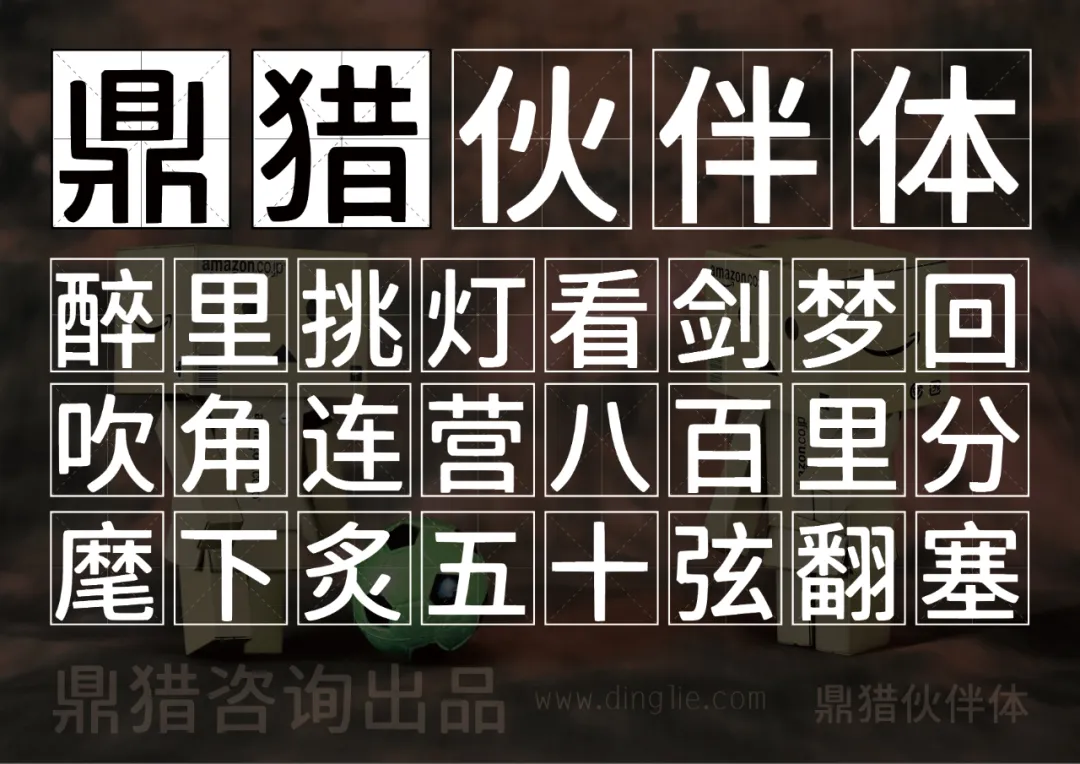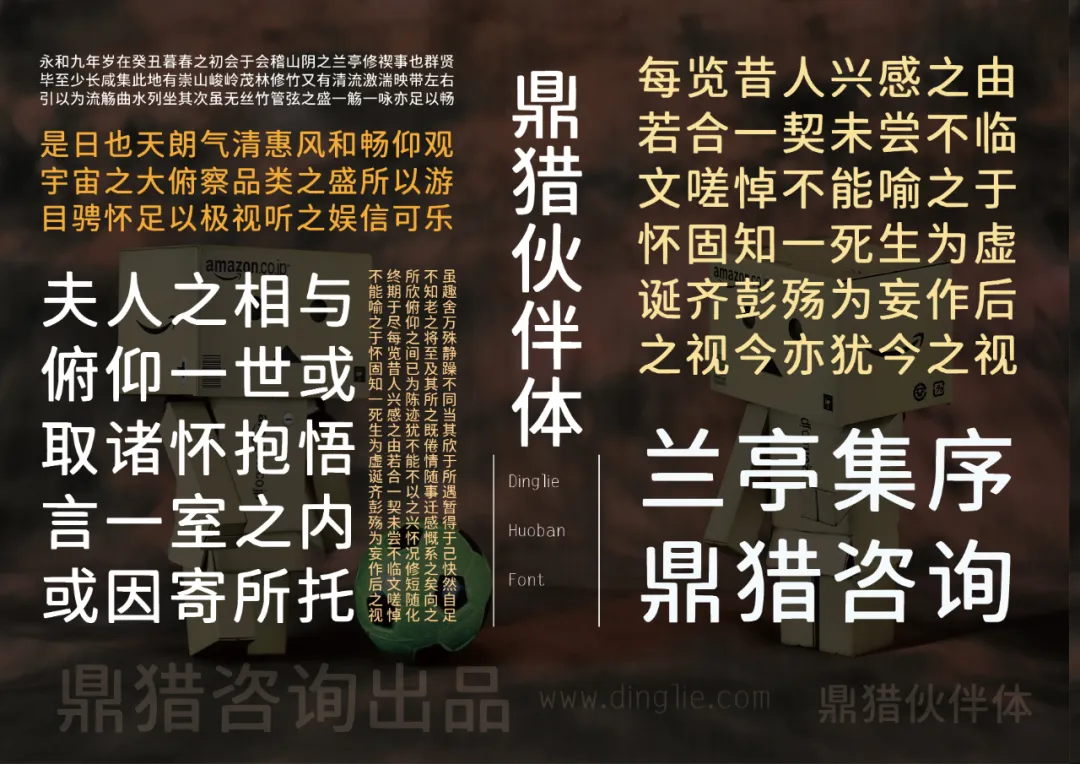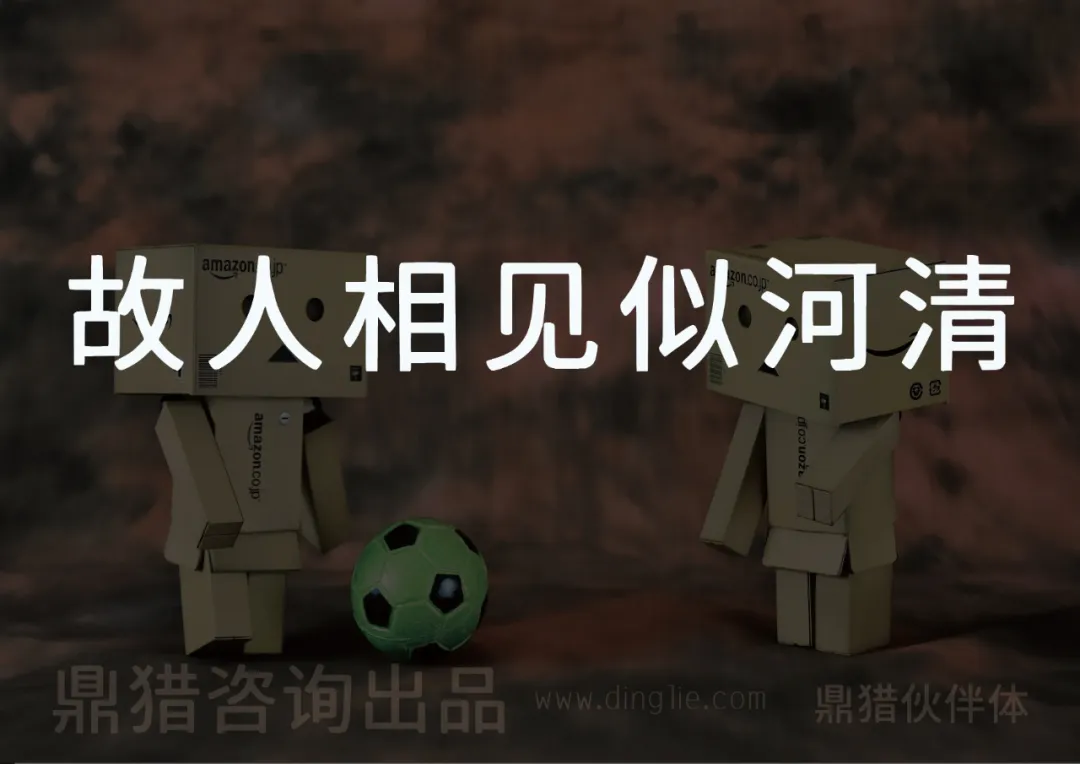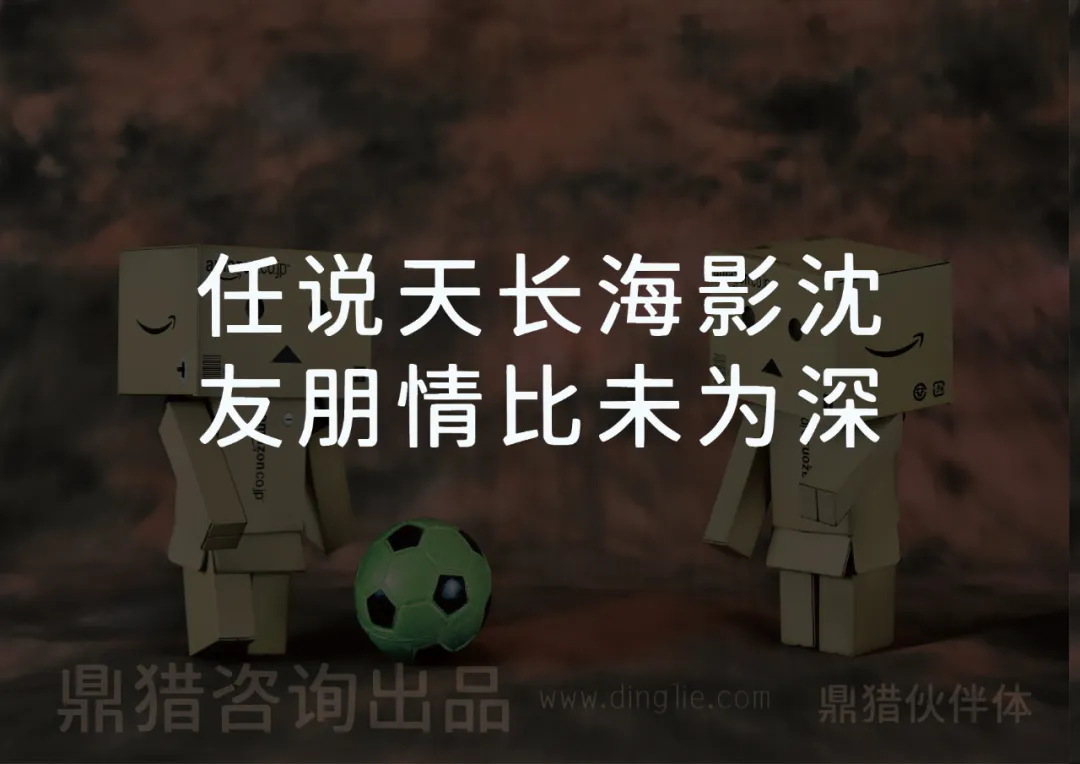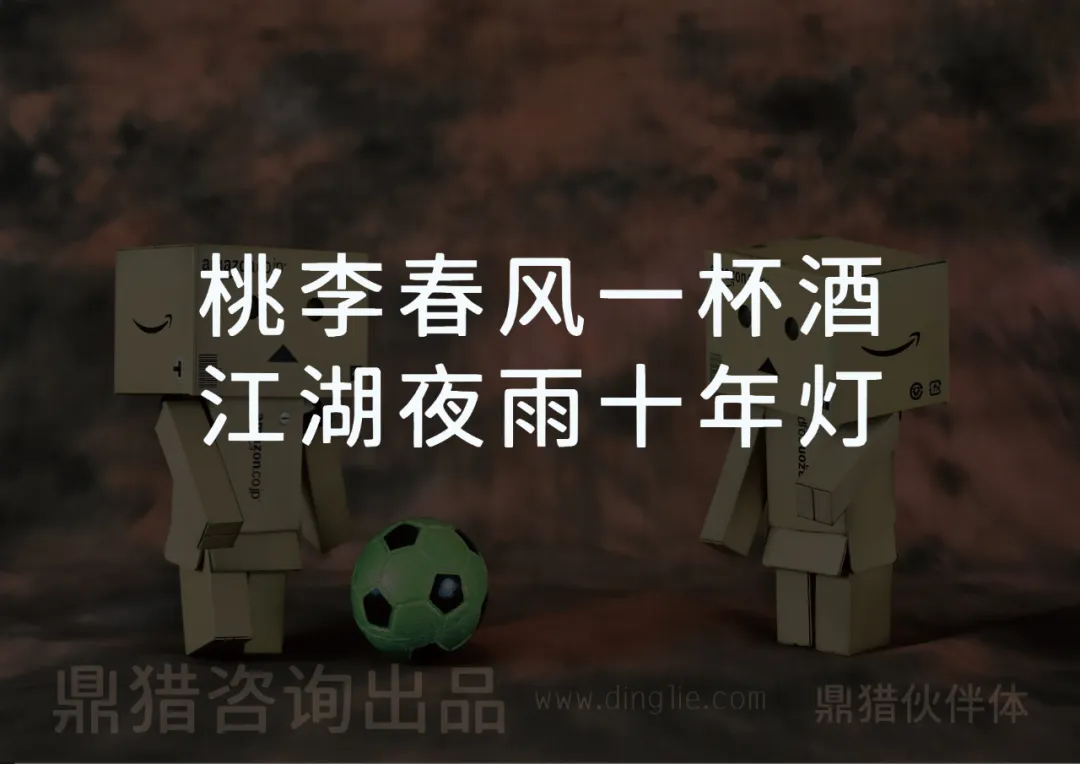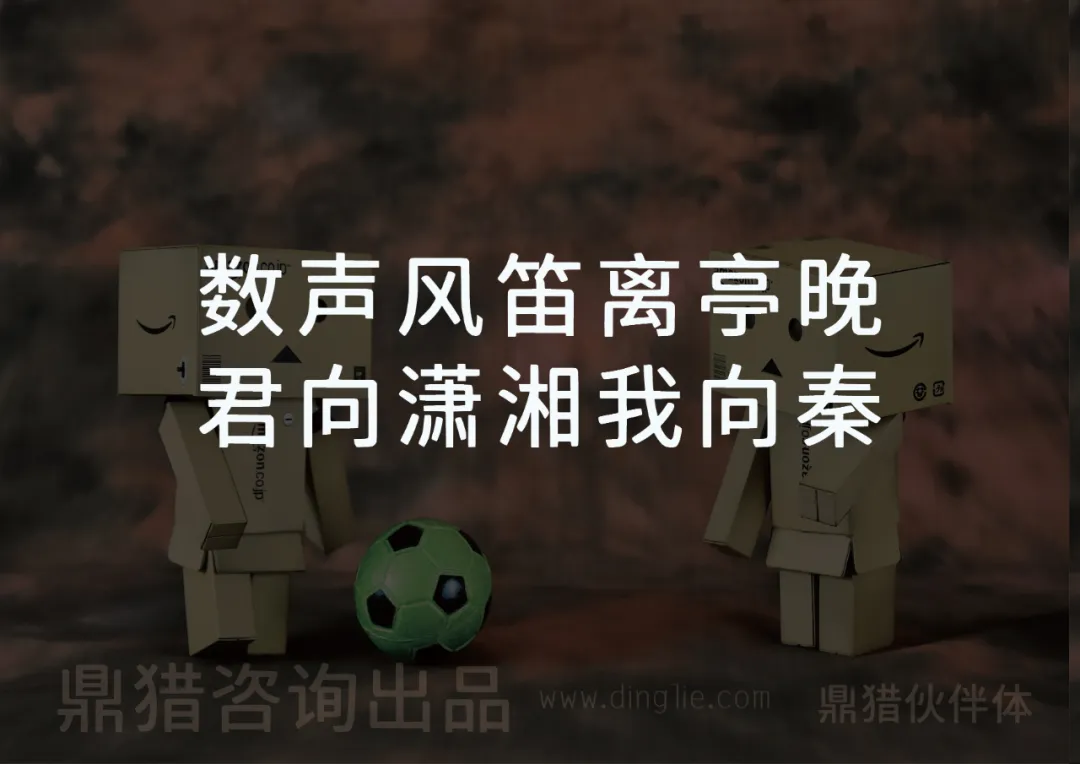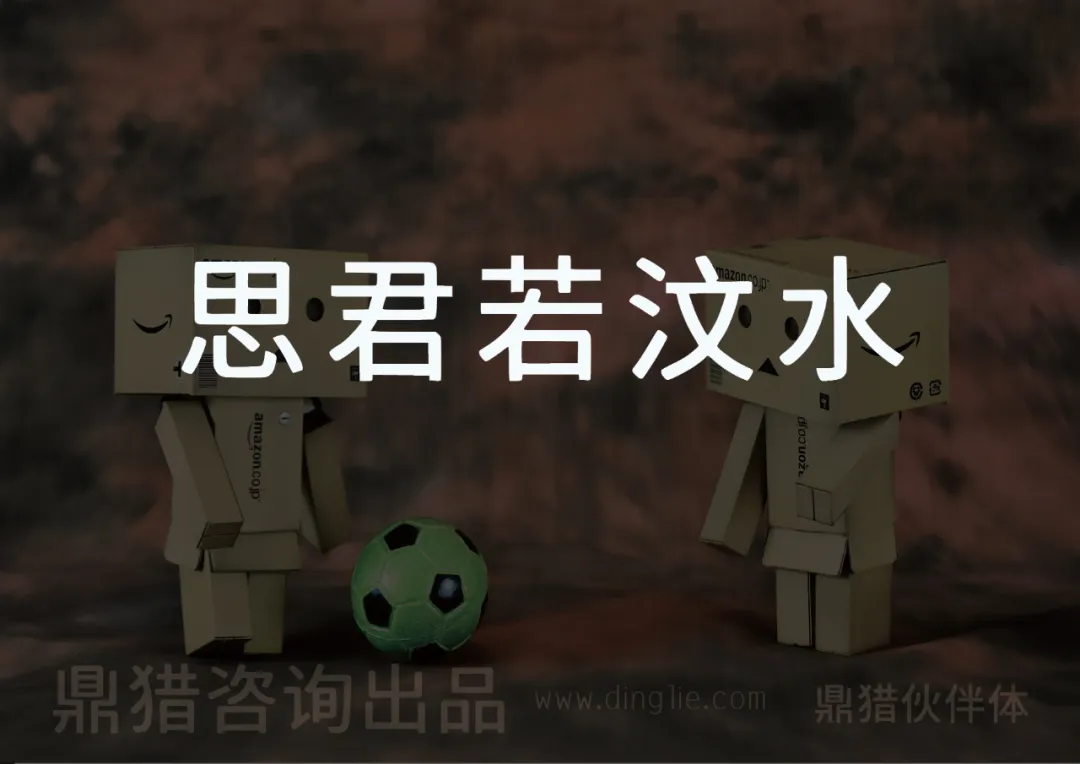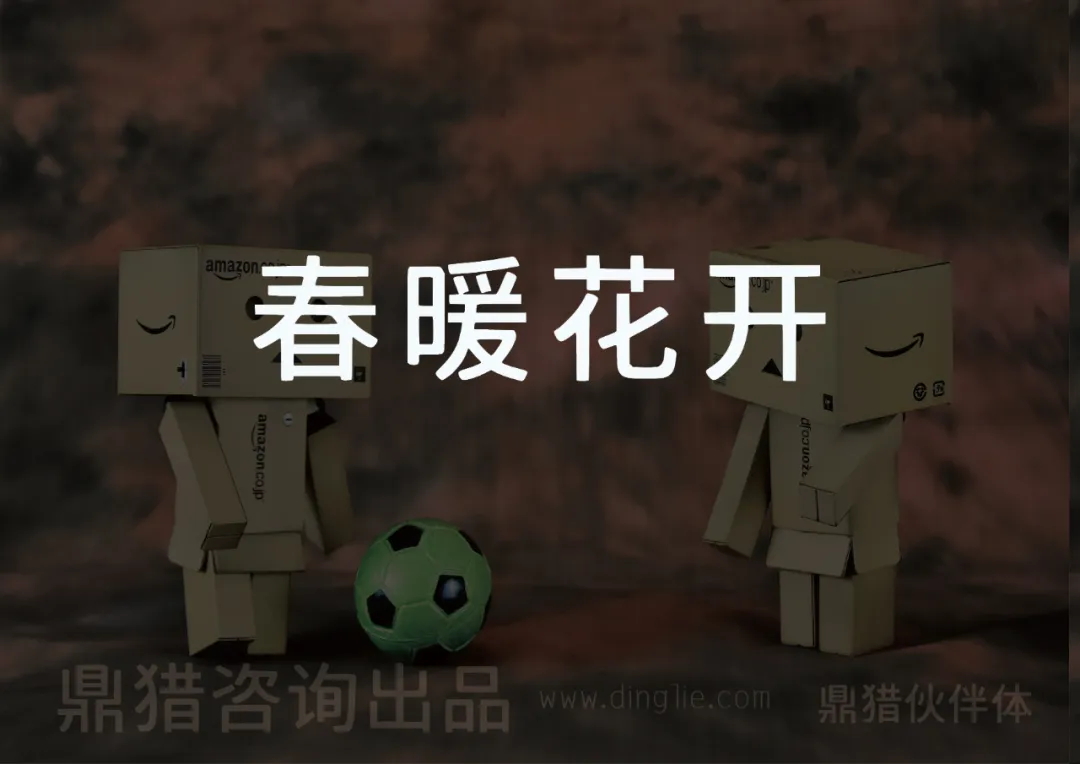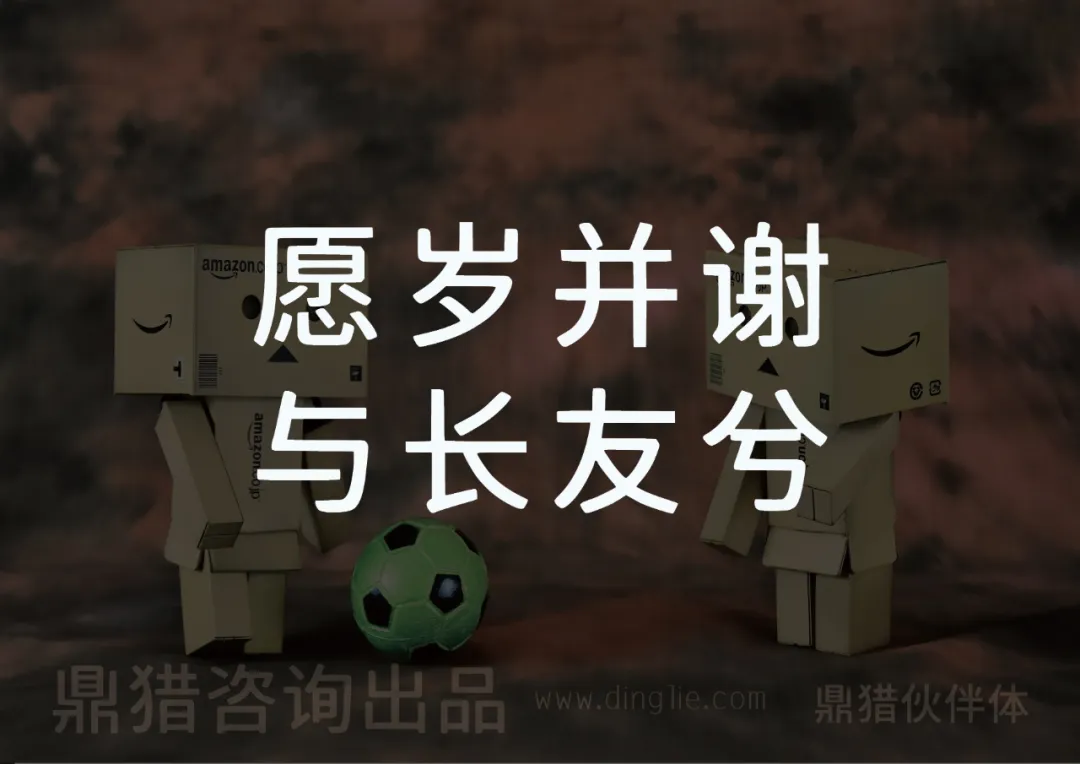
鼎猎伙伴体,为一款原创多应用场景黑体字,适合美食餐饮、文化艺术展览、企业文化,以及封面杂志海报、餐饮茶饮、美妆护肤等各个行业。
鼎猎伙伴体字体展示,包含诗句醉里挑灯看剑梦回吹角连营八百里分麾下炙五十弦翻塞,底部标注鼎猎咨询出品及网址-刊刻Kntuk
考虑到字体应尽可能满足各类型的姓和名,
鼎猎伙伴体以简体中文汉字编码国家标准(GB2312编码)为标准,
共计设计了多达7415个字符,其中汉字6769个。
可以满足绝大部分印刷设计等要求。
鼎猎伙伴体字体展示《兰亭集序》内容,由鼎猎咨询出品-刊刻Kntuk
两个纸箱人隔着绿色足球相对而立,配文故人相见似河清,底部有鼎猎咨询出品及网址-刊刻Kntuk
两个纸箱人中间有一个足球,配文任说天长海影沈友朋情比未为深,底部标注鼎猎咨询出品www.dinglie.com鼎猎伙伴体。-刊刻Kntuk
两个纸箱人与足球旁配有文字“桃李春风一杯酒 江湖夜雨十年灯”,底部标注“鼎猎咨询出品 www.dinglie.com 鼎猎伙伴体”。-刊刻Kntuk
两个纸箱人站在足球旁,图上写着“数声风笛离亭晚 君向潇湘我向秦”,底部有“鼎猎咨询出品 www.dinglie.com 鼎猎伙伴体”-刊刻Kntuk
画面显示两个纸箱人和一个足球,上方有“思君若汶水”字样,底部有“鼎猎咨询出品”及www.dingle.com-刊刻Kntuk
两个印有亚马逊标志的纸箱人站在足球旁,配文“春暖花开”,底部标注“鼎猎咨询出品”及网址。-刊刻Kntuk
愿岁并谢与长友兮,鼎猎咨询出品,www.dingle.com,鼎猎伙伴体,两个纸箱人与足球。-刊刻Kntuk